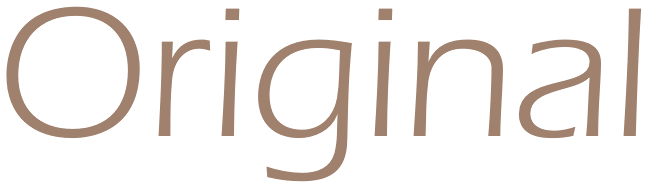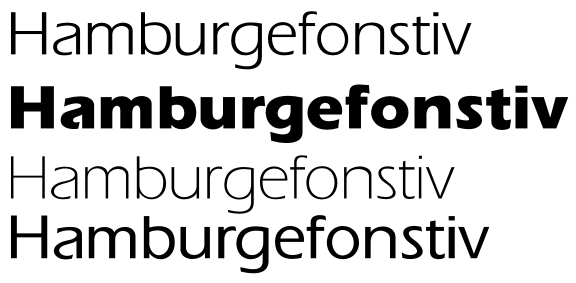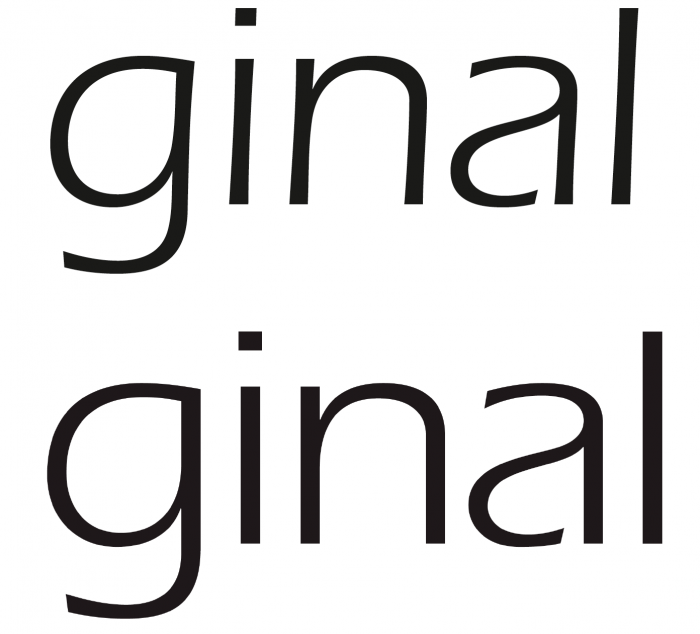
Ich suche eine senkrechte Eras … gibt es die?
Nikkiso verwendet sie für ihren Claim, mag sein, dass das auch von Hand hingezupft wurde. Kennt jemand eine?
Ui, danke :-) Wie könnte ich denn an die Version 1.000 kommen, war die irgendwo dabei?
Ich hege ja die Hoffnung, dass jemand die beispielsweise auf einer uralten Adobe-CD hat, die man käuflich erwerben könnte … oder so ähnlich.
Nö, die unterscheiden sich leider auch im Duktus, die aktuelle Eras hat konkave Verjüngungen bei senkrechten Elementen, die Ur-Version ist parallel.
Okay, dann ist das wirklich diese Low-Res-Zeichnung und nicht nur ein falsch eingestellter Parameter. Dann wird’s wohl umso schwerer, das Ding aufzutreiben.
Bei den Schriften von CorelDraw 2 (also vor ca. 20 Jahren) gab es eine gerade Eras welche allerdings Erie genannt wurde. Damals noch unter einen speziellen Schriftenformat.
Die Eras/Erie von Corel 3 war dann im TrueType-Format allerdings schon leicht abgeschrägt. Nur eine Erie Bold, welche man heute noch leicht über eine Googlesuche finden kann stand weiterhin aufrecht.
Da bei mir Corel 2 im Windows XP-Modus noch läuft, könnte ich wenn es nur ein paar Wörter sind selbige absetzen und als EPS speichern.
Warum Corel 2? Warum XP-Modus? Du hast die Schrift doch als Font auf der CD? Oder kannst Du die nicht parallel installieren? Aber Im Prinzip ist das doch vollkommen egal. Den Scjriftzug mit dem Font kannst Du doch auch aus einem Fonteditor raus in eine EPS-Datei schreiben. Heb einfach nur den Originaldatenträger mit den Fontdateien auf und gut ist's. Der Rest findet sich dann ...
CorelDraw 2 hatte ein spezielles Schriftformat dieses heißt *.wfn und arbeitet nur mit CorelDraw Version 2 zusammen (ev. klappte es auch noch mit Version 3 aber mit neuen Versionen bestimmt nicht mehr).
Zwar gibt es bei Corel 2 ein Hilfsprogramm mit dem man die WFN-Schriften in Type1 konvertieren kann und mit Fontforge hab ich es dann in OpenType konvertiert. Aber die frühen Corelschriften hatten ohnehin nicht den besten Ruf und ob mehrmaliges Konvertieren der Schrift so gut tat?
Außerdem benötige ich Corel 2 ohnehin da ich so zwei- bis dreimal im Jahr auf verschiedene uralte Coreldateien zugreifen muß welche in neueren Versionen ebenfalls nicht zu öffnen sind.
Unten ein vielsagendes Bildschirmfoto … (naja damals sah man das nicht so streng ;-) )
Wobei ich für den Konvertiervorschlag bestimmt gleich Haue von den EULA-Verfechtern bekomme :D